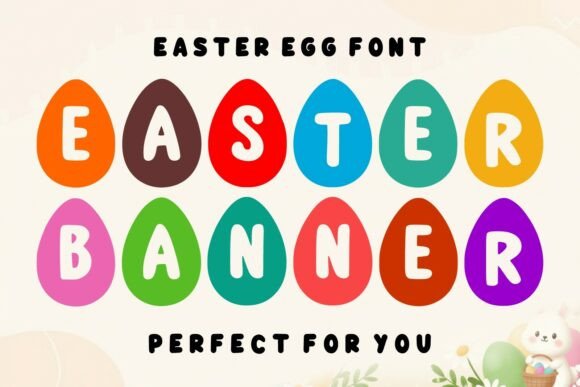
Easter Banner
Het vinden van de juiste ontwerpelementen kan lastig zijn, maar Easter Banner biedt een uitzonderlijke collectie die uw werk direct naar een hoger niveau tilt.